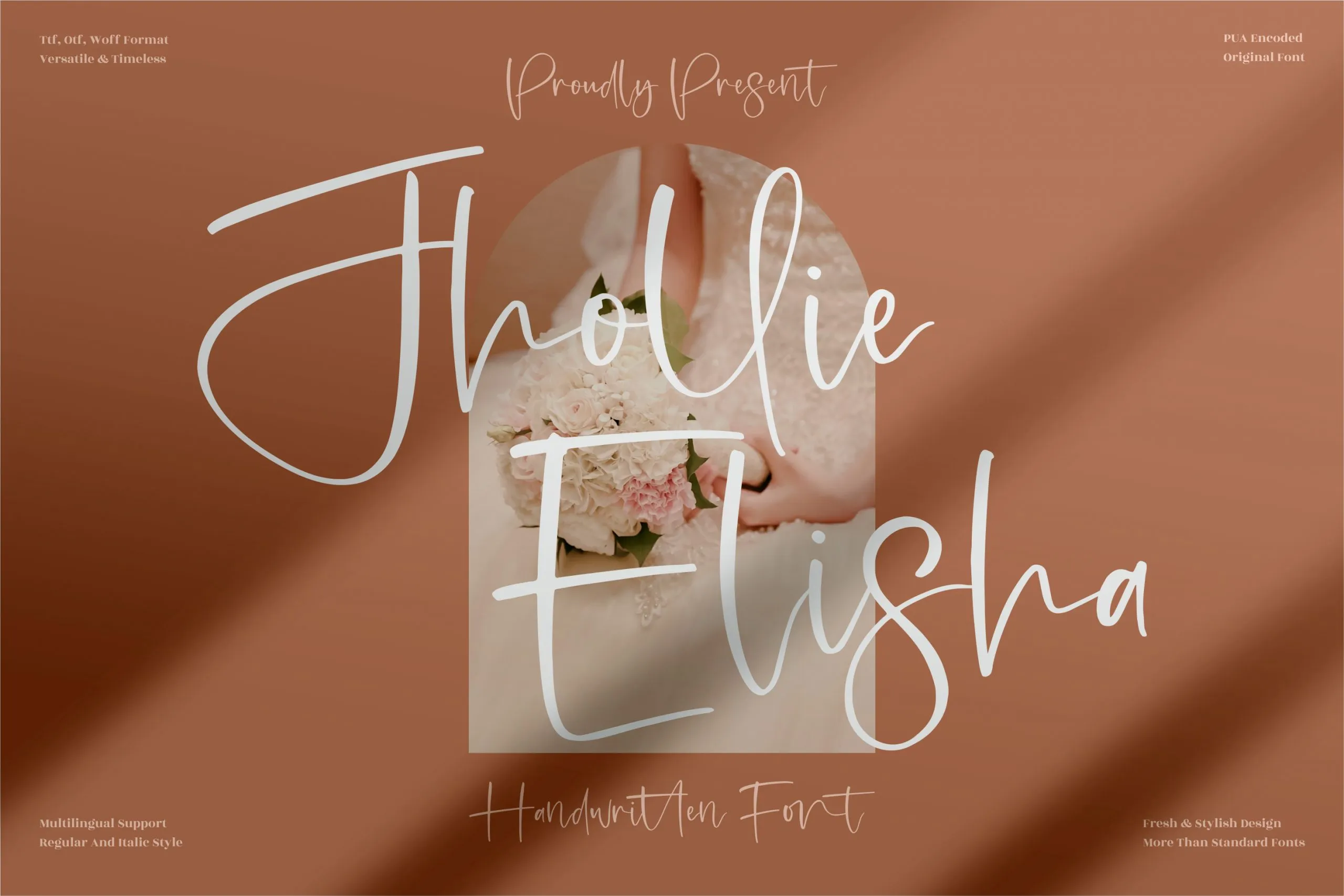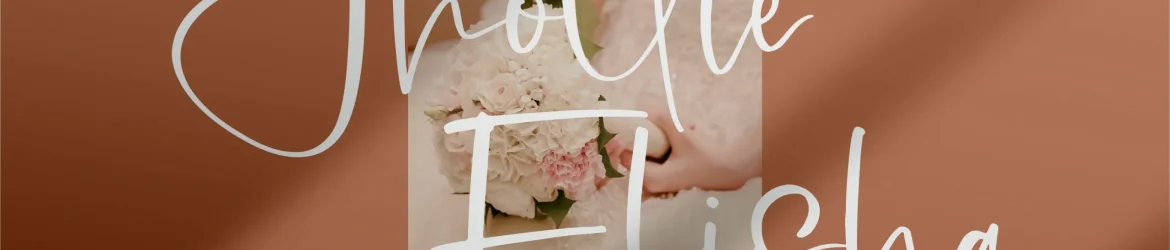
Jhollie Elisha Font – Download Grátis
A Jhollie Elisha Font é uma fonte escrita a mão perfeitamente adaptada para diversos projetos criativos na cena brasileira. Suas linhas espalhadas e expressivas permitem que qualquer projeto, desde design de marca até embalagens de produtos, tenha um toque autêntico e pessoal. Este estilo único traz uma sensação acolhedora e natural à sua obra, tornando-a perfeitamente adaptável para criar identidades visuais únicas, designs de produto envolventes e itens de decoração que despertem sentimentos em quem as usa. A Jhollie Elisha Font é o ideal para qualquer projeto que deseje trazer um toque de autenticidade e humanização à sua arte. Com a sua capacidade de adaptar-se a uma variedade de projetos, seja ela escrita com carinho para etiquetas personalizadas ou para fazer o texto de um cartão de convite ganhar vida própria, esta fonte criativa será certamente uma adição valiosa ao seu portfolio. E se você está procurando por uma maneira especial de trazer sua marca para a frente, isso é o caminho perfeito.